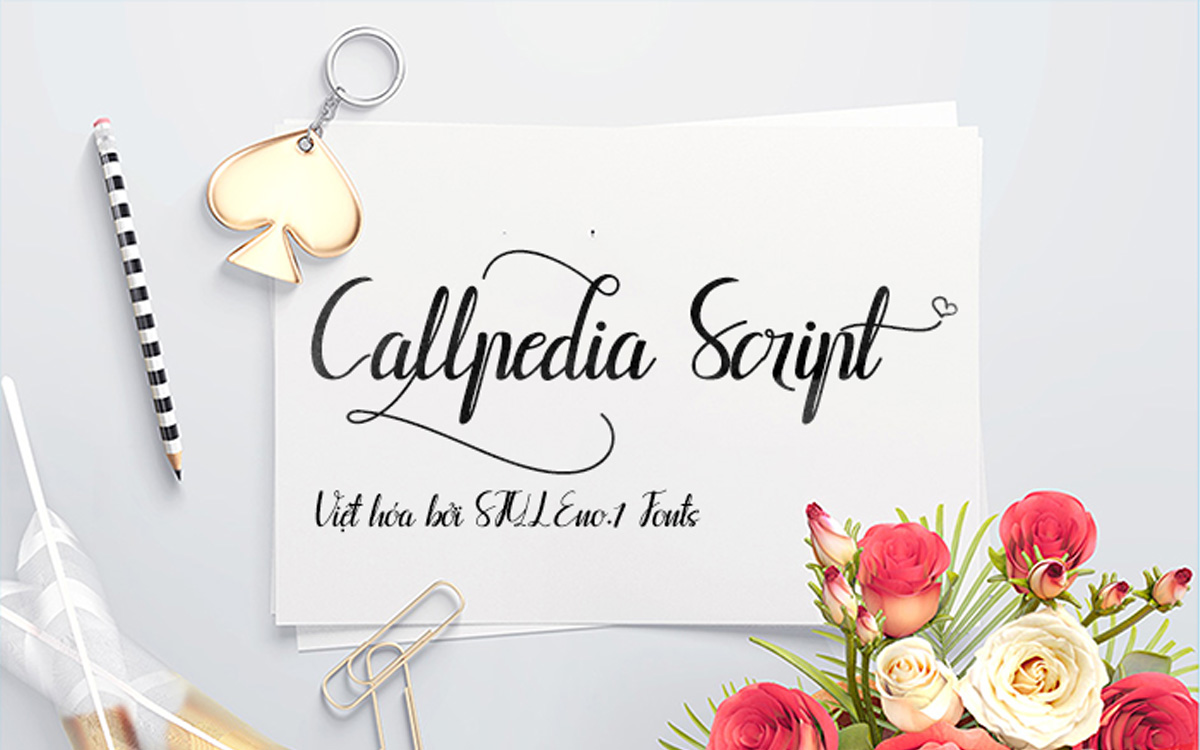
Font chữ viết tay, chữ ký mềm mại cho thiệp cưới, đám cưới SVN-Callpedia
Font chữ viết tay, chữ ký mềm mại cho thiệp cưới, đám cưới SVN-Callpedia là một trong những bộ font nghệ thuật đỉnh cao, được chế tác tỉ mỉ dành riêng cho các thiết kế mang phong cách lãng mạn và sang trọng. Với đường nét nét thanh nét đậm chuẩn phong cách thư pháp hiện đại (modern calligraphy), bộ font này truyền tải trọn vẹn cảm xúc chân thành, tinh tế trong từng lời mời sự kiện trọng đại. Đặc biệt, phiên bản SVN-Callpedia đã được Việt hóa hoàn chỉnh, giúp bạn dễ dàng tạo nên những mẫu thiệp cưới độc đáo mà không gặp bất kỳ lỗi hiển thị tiếng Việt nào.
Trải Nghiệm Đỉnh Cao Với Font Chữ Viết Tay, Chữ Ký Mềm Mại Cho Thiệp Cưới, Đám Cưới SVN-Callpedia Việt Hóa
Trong xu hướng thiết kế thiệp cưới hiện đại, sự lên ngôi của các dòng font chữ viết tay (handwritten font) và chữ ký (signature font) đã tạo nên một làn gió mới, thay thế cho những nét chữ in đứng truyền thống cứng nhắc. Font chữ viết tay, chữ ký mềm mại cho thiệp cưới, đám cưới SVN-Callpedia chính là giải pháp hoàn hảo giúp nâng tầm thẩm mỹ cho toàn bộ bộ nhận diện tiệc cưới của bạn. Từ khâu thiết kế thiệp mời, bảng đón khách (welcome board) cho đến thực đơn tiệc cưới hay thiệp cảm ơn, SVN-Callpedia đều mang lại vẻ đẹp thanh lịch, đẳng cấp và đậm chất cá nhân hóa.
Điểm làm nên sự khác biệt của SVN-Callpedia so với các font chữ thông thường chính là nhịp điệu chuyển động tự nhiên giữa các nét chữ. Nhờ kỹ thuật tinh chỉnh khoảng cách ký tự (kerning) chuẩn xác và cấu trúc nét nối mượt mà, font chữ tạo cảm giác như một tác phẩm nghệ thuật được viết tay trực tiếp bởi những nghệ nhân calligrapher chuyên nghiệp. Đây chính là yếu tố then chốt giúp bộ font này chiếm trọn trái tim của các nhà thiết kế đồ họa, các đơn vị in ấn thiệp cưới và các cặp đôi sắp về chung một nhà.
1. Đường Nét Thư Pháp Mềm Mại, Bay Bổng Và Mang Tính Nghệ Thuật Cao
SVN-Callpedia sở hữu nét chữ uốn lượn tự nhiên với sự kết hợp hài hòa giữa nét thanh mảnh và nét đậm uyển chuyển. Cấu trúc chữ được thiết kế dựa trên kỹ thuật viết bút lông thư pháp (brush lettering), tạo ra những khoảng hở nghệ thuật và độ nghiêng hoàn hảo. Sự tinh tế này giúp tiêu đề thiệp cưới, tên cô dâu chú rể trở nên nổi bật, quyến rũ và dễ dàng thu hút ánh nhìn đầu tiên của người nhận.
2. Hỗ Trợ Đầy Đủ Tiếng Việt Unicode Chuẩn Và Hệ Thống Glyphs Phong Phú
Một trong những ưu điểm vượt trội nhất của phiên bản SVN-Callpedia là khả năng hỗ trợ tiếng Việt trọn vẹn với đầy đủ hệ thống dấu câu được xử lý khéo léo. Các dấu thanh như sắc, huyền, hỏi, ngã, nặng hay các dấu phụ trên ký tự ê, ơ, ư đều được thiết kế tỉ mỉ để không làm đứt gãy nét uốn lượn tự nhiên của chữ. Bên cạnh đó, font chữ còn tích hợp hệ thống ký tự thay thế (alternate glyphs), ký tự nối (ligatures) và đuôi chữ hoa mỹ (swashes), cho phép người dùng tùy biến chữ ký hoặc tên riêng một cách ấn tượng nhất.
3. Ứng Dụng Đa Dạng Trong Thiết Kế Ấn Phẩm Tiệc Cưới Và Nhận Diện Thương Hiệu
Không chỉ giới hạn trong phạm vi thiệp cưới, font chữ SVN-Callpedia còn là sự lựa chọn lý tưởng cho nhiều loại ấn phẩm cao cấp khác. Bạn có thể sử dụng bộ font này để làm logo thương hiệu váy cưới, thiết kế nhãn mác nước hoa, bao bì mỹ phẩm, bìa sách lãng mạn, bài đăng mạng xã hội hay các loại thiệp mời sự kiện cao cấp (gala dinner, sinh nhật, anniversary). Sự linh hoạt của SVN-Callpedia giúp mọi sản phẩm thiết kế đều khoác lên mình vẻ thanh lịch và đầy cảm xúc.
4. Tương Thích Tốt Trên Mọi Phần Mềm Thiết Kế Và Phương Pháp In Ấn
5. Tối Ưu Trải Nghiệm Thị Giác Cho Cả Sản Phẩm In Ấn Và Kỹ Thuật Số
Dù thể hiện trên giấy mỹ thuật cao cấp, giấy đệm gân hay hiển thị trên màn hình smartphone, tablet trong các mẫu thiệp cưới online (e-invitation), SVN-Callpedia vẫn giữ nguyên độ sắc nét và tính thẩm mỹ cao. Font chữ giúp cân bằng giữa yếu tố trang trí bay bổng và khả năng đọc (readability), đảm bảo khách mời vừa cảm nhận được sự trang trọng vừa dễ dàng nắm bắt thông tin quan trọng về ngày vui của bạn.
Bí Quyết Phối Font SVN-Callpedia Để Tạo Ra Mẫu Thiệp Cưới Hoàn Hảo
Để tận dụng tối đa vẻ đẹp của font chữ viết tay, chữ ký mềm mại cho thiệp cưới, đám cưới SVN-Callpedia, bạn có thể áp dụng các quy tắc kết hợp font chuyên nghiệp dưới đây:
• Sử dụng SVN-Callpedia cho thành phần chính: Hãy dùng font chữ này cho tên cô dâu & chú rể, chữ “Thiệp Mời”, hoặc tiêu đề các mục lớn để tạo điểm nhấn thị giác mạnh mẽ nhất.
• Kết hợp với font Sans-serif hoặc Serif tối giản: Đối với các thông tin chi tiết như ngày giờ, địa điểm, rạp cưới, hãy kết hợp SVN-Callpedia với một font chữ không chân (Sans-serif) mảnh hoặc font có chân (Serif) cổ điển để tổng thể thiết kế hài hòa, dễ đọc.